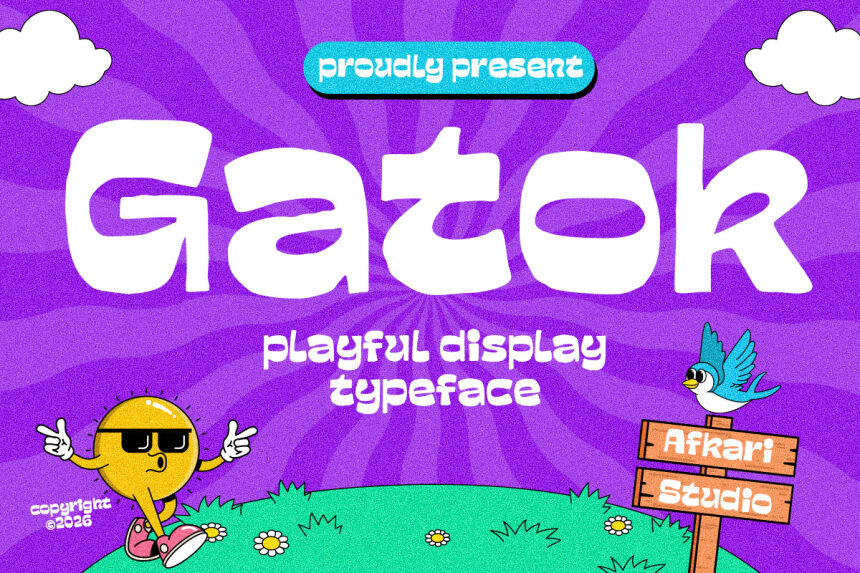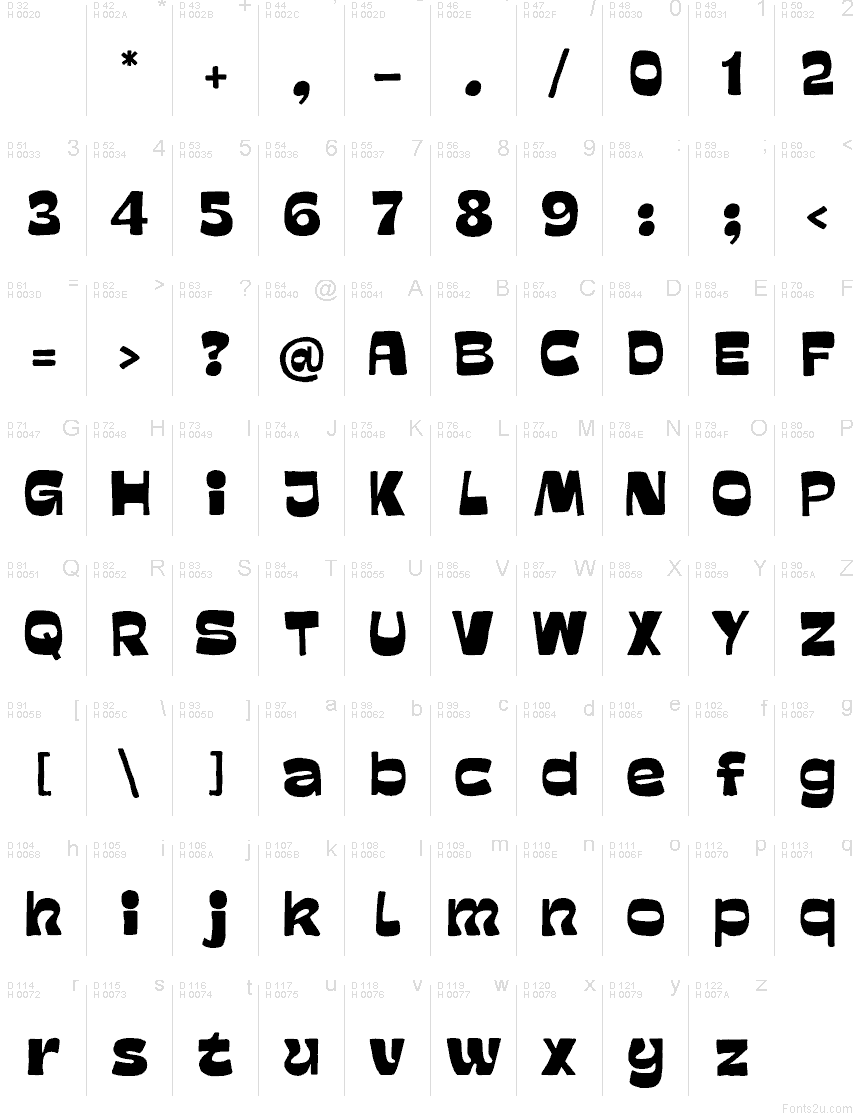
Gatok, de Afkari Studio, es una tipografía display retro gratuita con una silueta contundente y suave, con ese aire característico de los años 70. Sus letras se sienten como si hubieran sido moldeadas a mano, con curvas amplias, uniones cerradas y un toque desenfadado que evita que la fuente se perciba rígida o demasiado pulida.
Encaja a la perfección en carteles, portadas de álbumes, branding para cafeterías, packaging y titulares llamativos en redes sociales, donde importa más un estilo vintage cercano que la perfección técnica. Al ser una fuente gratuita, Gatok funciona de maravilla para títulos cortos o encabezados, ya que esas formas anchas y redondeadas lucen mejor en textos breves que buscan transmitir un ambiente cálido, informal y con un toque funky.